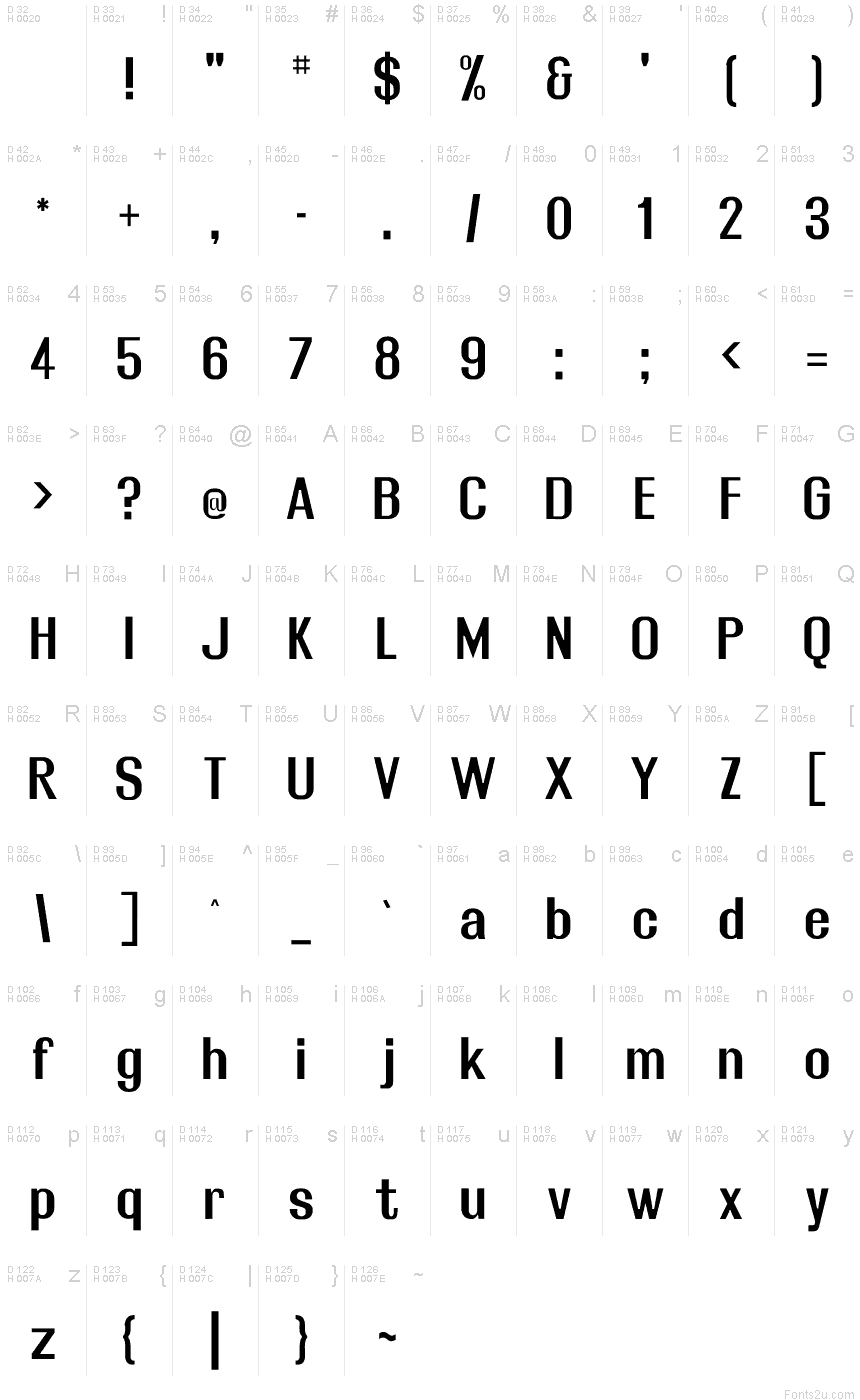
Rollout Semibold
Rollout Semibold autorstwa Bena Weinera to darmowy geometryczny krój bezszeryfowy z wyrazistym nawiązaniem do stylu Art Déco. Wąskie, owalne zaokrąglenia i wysokie, niemal architektoniczne pionowe kreski nadają literom dynamiczny, opływowy rytm. Prostota kroju osadza go w estetyce cyfrowego projektowania późnych lat 90., unikając przy tym wrażenia retro pastiszu.
To naturalny wybór darmowego fontu do nagłówków na plakatach, okładek czasopism, opakowań płyt, projektów identyfikacji wizualnej oraz plansz tytułowych, gdzie potrzebna jest zwarta, strzelista sylwetka. Świetnie sprawdza się również w monogramach i krótkich logotypach, ponieważ powtarzające się zaokrąglone formy tworzą czyste wizualne echo, nie sprawiając wrażenia zbyt miękkich czy swobodnych.